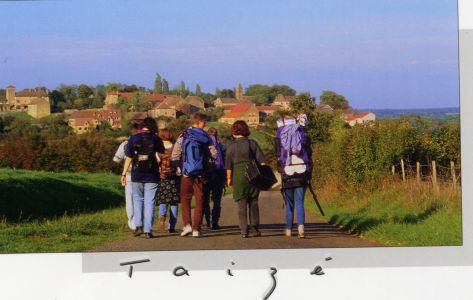
Welche Schriftart ist auf dieser Postkarte
Welche Schriftart ist das und kann man sie irgendwo runterladen?
neee, ist sie nicht. aber recht haste trotzdem.
Nein, natürlich ist sie es nicht.
Die Elegance ist natürlich schöner.
Sie ist angelehnt an die Original-Handschrift von Karlgeorg Hoefer.
Otmar Hoefer schreibt auf seiner Webseite darüber.
Welche ist es denn dann??
Das Z sieht auf der Karte anders aus, als in deiner Abbildung, oder ist das kein Z, sondern ein anderes Zeichen?
Kann man sich die Schrift irgendwo herunterladen?
Oh, nicht nur das z sieht anders aus. Auch das T und alle anderen Lettern.
Aber das liegt nur daran, daß es sich bei Deiner Schrift nicht um die Elegance handelt. Sie hat nur dieselbe Anmutung des Handschriftlichen.
Ob es die Elegance als Font gibt, kann ich Dir leider nicht sagen.
Gibt es denn eine, der auf der Karte ähnliche Schrift zum Download?
Schreib' doch schnell die fünf Buchstaben und scan sie ein.
damit wir dir auch 'ewtas' geholfen haben:
such mal im netz nach der schrift "Alpha Mack" von Astigmatic One Eye
die ist kostenlos und kommt deiner schrift nah. aber halt nur nah.
Da geht es wohl sehr rustikal, schlicht, einfach zu und insofern passt die handschriftartige Schrift auf der Postkarte zum Pfadfinderlager/Jugendherbergsimage.
Das alberne Sperren beweist ja, daß es keine echte Handschrift ist, sondern nur auf einer basiert.